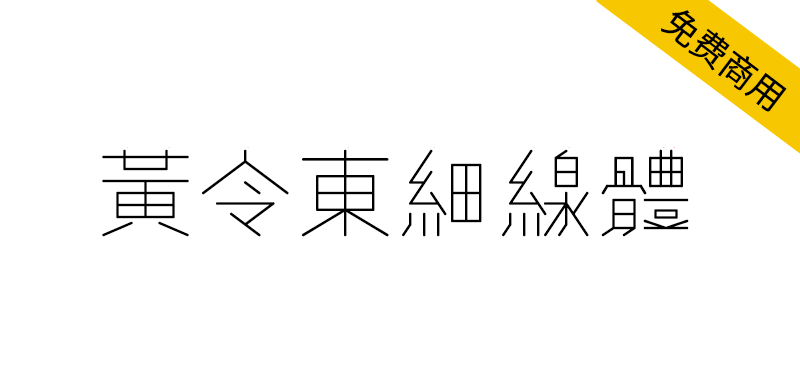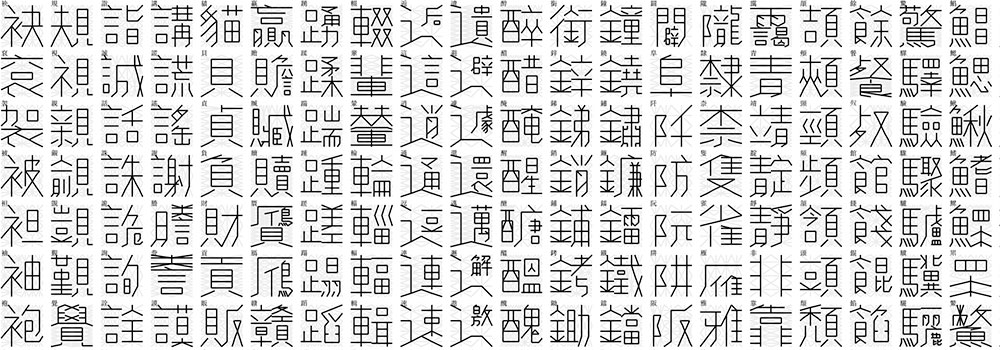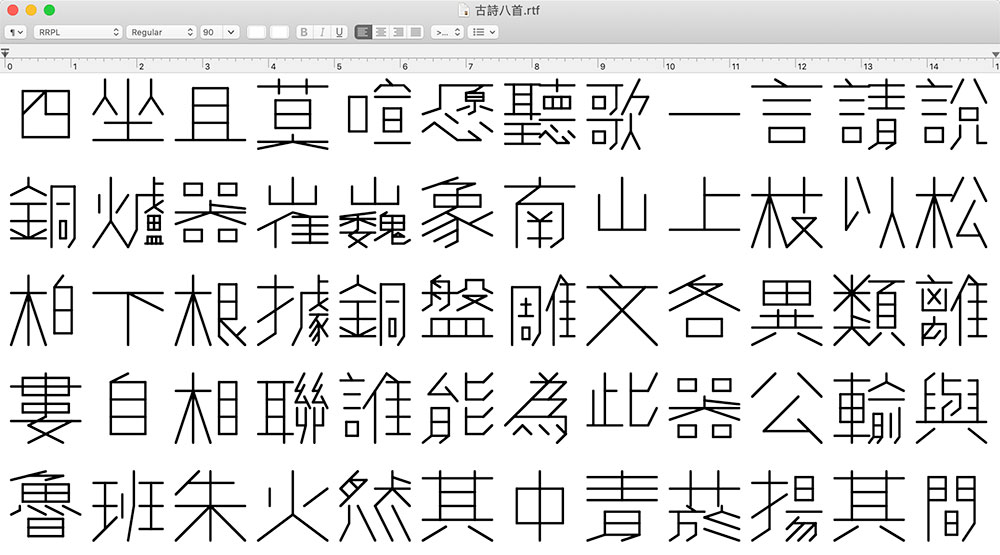
黄令东细线体(RRPL),由程序自动生成,用递归根式包装语言(RRPL)进行编写。在RRPL中,每个汉字被描述为数字、符号和对其他字符的引用的短字符串。它的语法灵感来自标记语言,如乳胶(LaTeX,一种基于ΤΕΧ的排版系统),以及传统的用于书法练习的“米”网格。使用5000+的繁体汉字和词根,其字形由默认解析器生成,由于是程序自动生成的字体,所以难免会有错别字,使用时要注意检查。
需要注意的是,由于是繁体的词根,所以输入简体字的话会直接映射成繁体字形。比如说你输入“国”字,会被成繁体的“國”字。